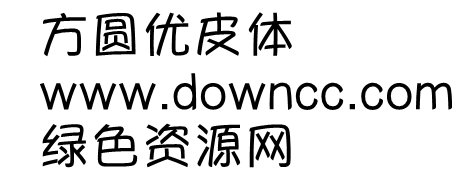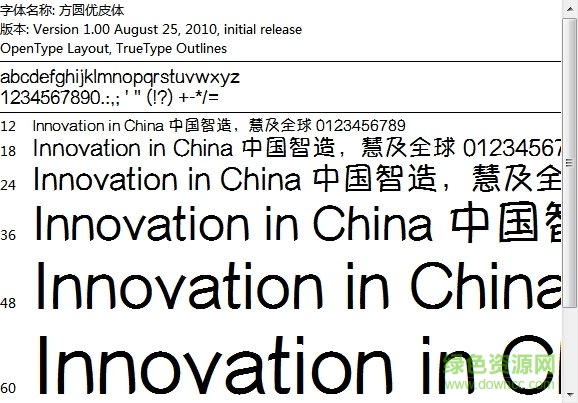
方圓優(yōu)皮體字體
方圓優(yōu)皮體方圓字體系列的一款十分圓潤(rùn)活潑的卡通字體,簡(jiǎn)潔圓滑的外觀讓文字更顯童真的特色,文字大方有著適當(dāng)程度的加黑,更顯明朗清晰,快來綠色資源網(wǎng)免費(fèi)體驗(yàn)吧!
方圓優(yōu)皮ttf字體特色
方圓優(yōu)皮體是一款可愛的卡通pop字體。具有手寫POP效果,趣味實(shí)足。適合POP設(shè)計(jì)、海報(bào)設(shè)計(jì)、兒童包裝、幼兒園展板等廣告設(shè)計(jì)使用。
方圓優(yōu)皮體ttf
方圓優(yōu)皮體是一款不常用的藝術(shù)字體,有著q萌圓潤(rùn)的可愛結(jié)構(gòu),將端正的線條和曲線的收尾結(jié)合起來,給你的平面設(shè)計(jì)、藝術(shù)設(shè)計(jì)、海報(bào)設(shè)計(jì)、包裝設(shè)計(jì)帶來更多特色魅力!